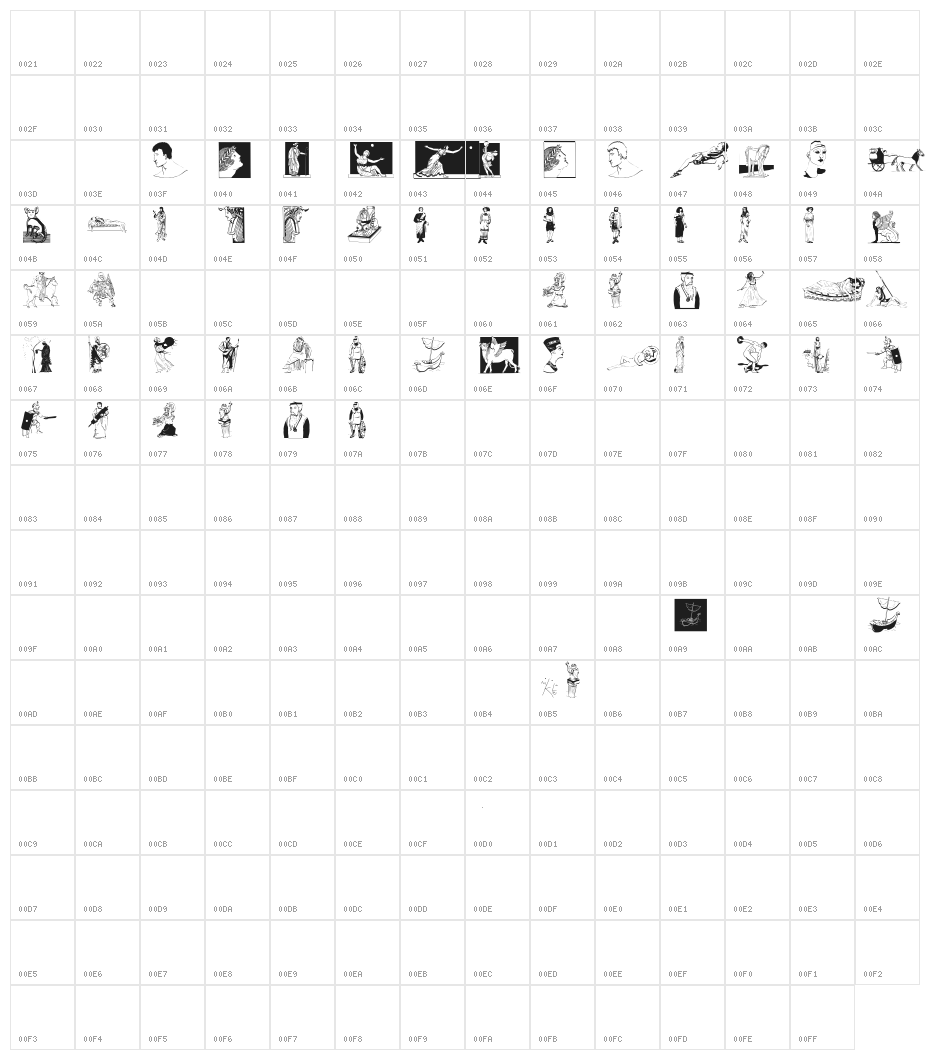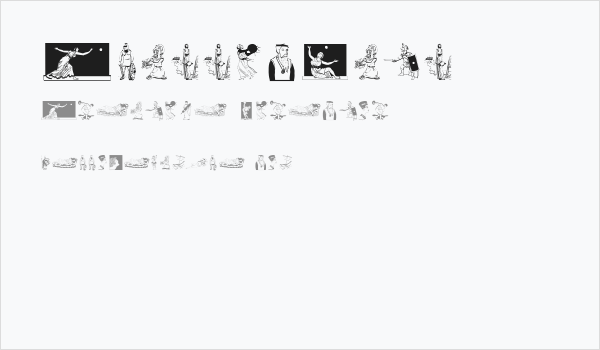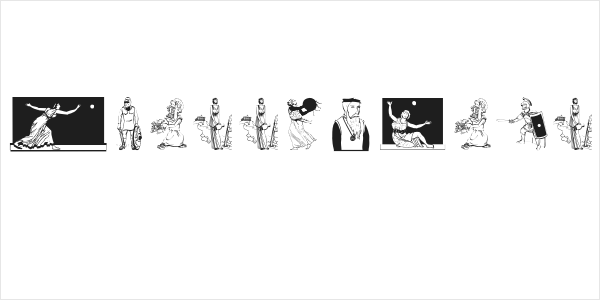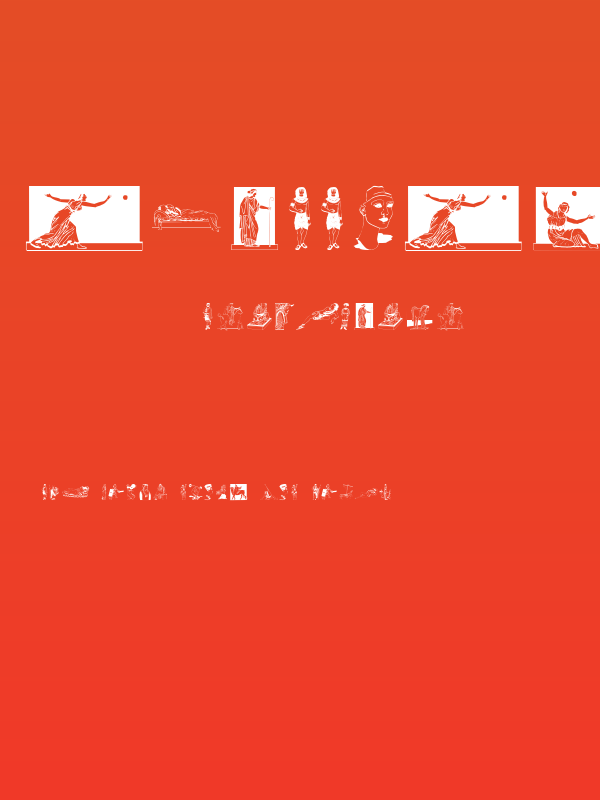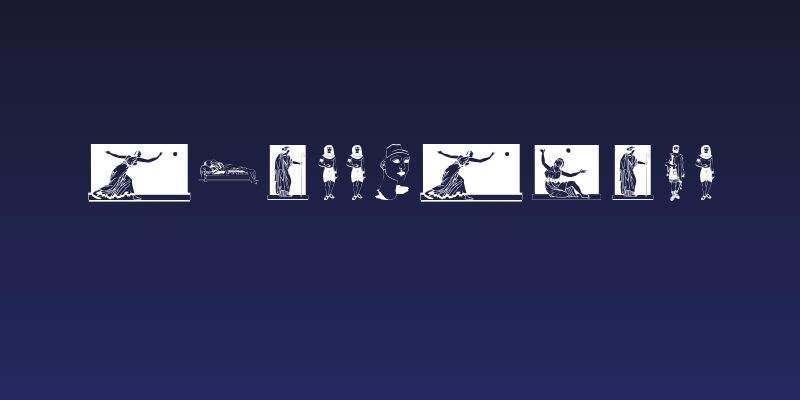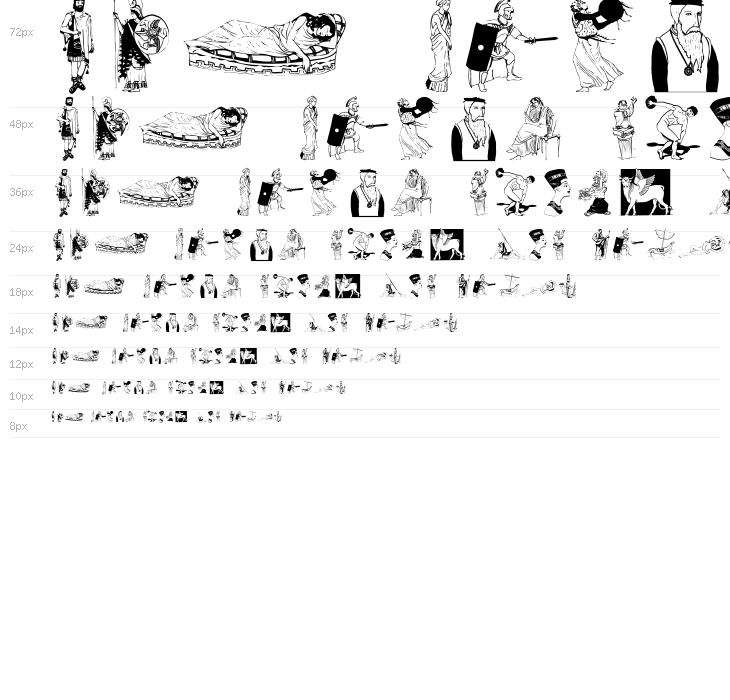
ClassicBats Font
| Anwendungsfall | Artistic projects, educational materials, themed designs. |
| Vorgeschlagene Projekte | Ideal for themed invitations, educational materials, historical presentations, or artistic projects that require classical imagery. |